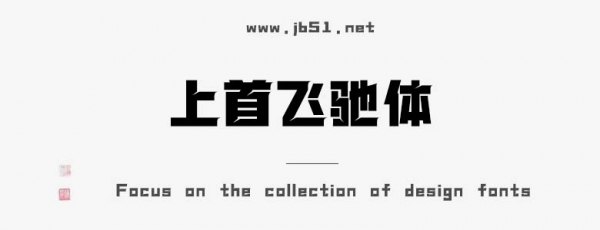
上首飛馳體是由上首造字字庫(kù)出品的字體,字體筆觸略粗,字形端正大氣,具有很好的視覺(jué)感,適合應(yīng)用于藝術(shù)設(shè)計(jì)、平面宣傳設(shè)計(jì)、網(wǎng)頁(yè)設(shè)計(jì),書(shū)法字帖等領(lǐng)域,需要的朋友可以前來(lái)本站下載。